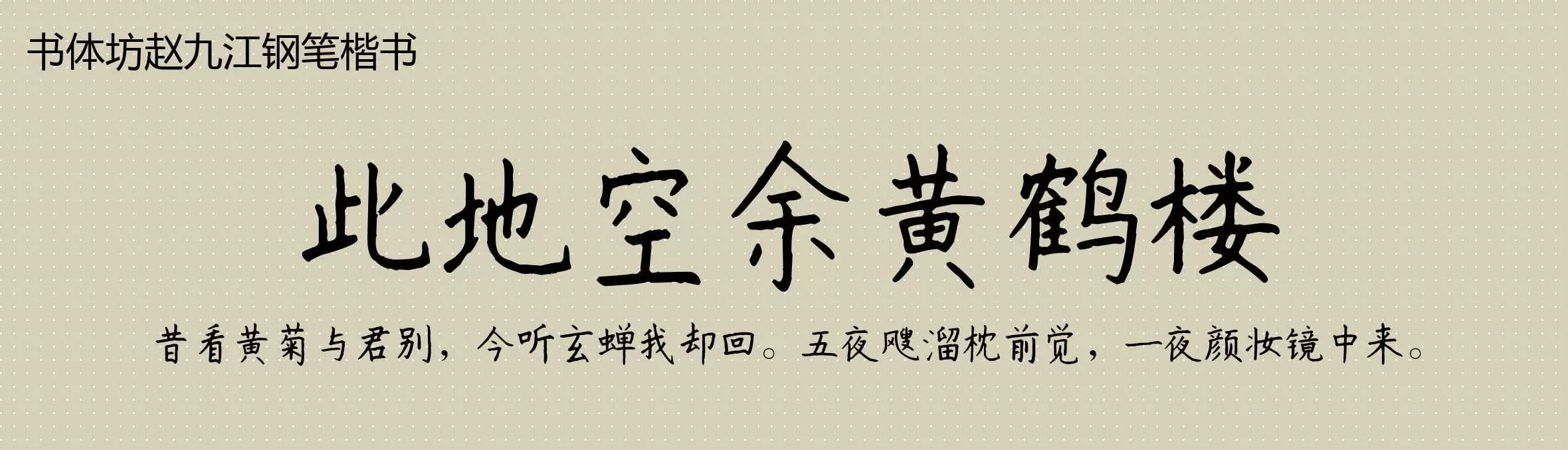
书体坊赵九江钢笔楷书是一种中文楷体字体,它是由中国知名书法家赵九江亲笔创作的。这个字体具有清秀流畅的笔画和端正规整的结构,非常适合用来书写公文或者正式文件。同时,它的笔画力度和韵律感也非常出色,特别适合用来书写短篇诗词或者书法作品。整体上来看,书体坊赵九江钢笔楷书是一种非常优秀的中文书体,它拥有独特的艺术价值和实用性,为广大书法爱好者和设计工作者提供了一个非常好的选择。